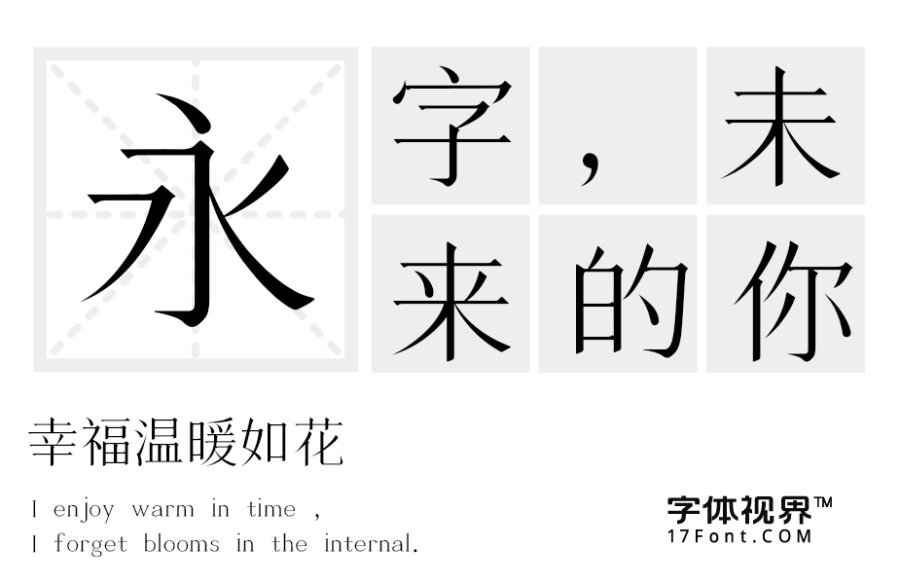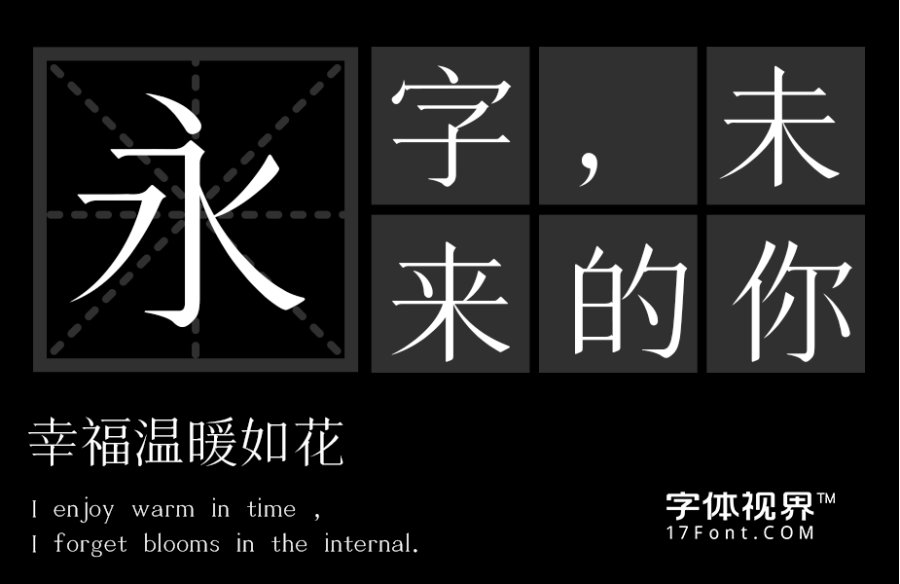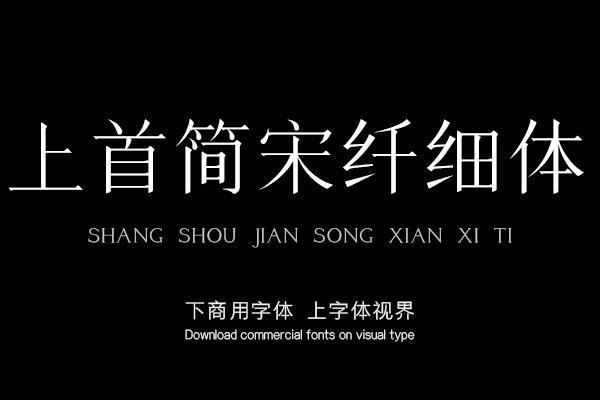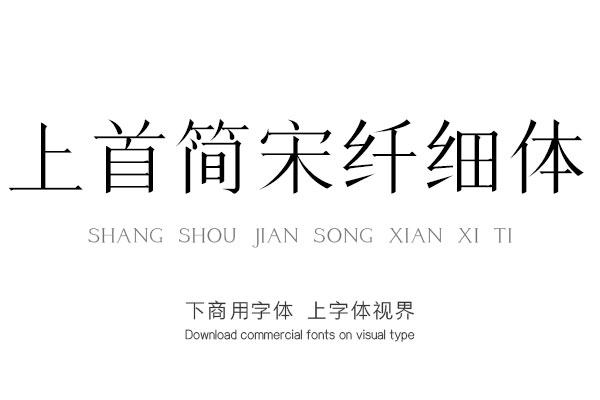
上首简宋纤细体,简体中文约6763字,字体粗细结合,顿错有致是此套字库的亮点。适用于搭配标志、广告标语、商业广告、正文等高端属性。购买须知:“下载服务费”与“字体VIP”所获得字体 仅用于个人非商用, 商用请联系付费授权。本字体为电脑用字,手机没有root权限不支持直接手机换字(手机如何root,请自行百度搜索教程)。购买前请先 了解清楚后再付款 ,字体为虚拟产品无法回收 一旦购买不支持退款。